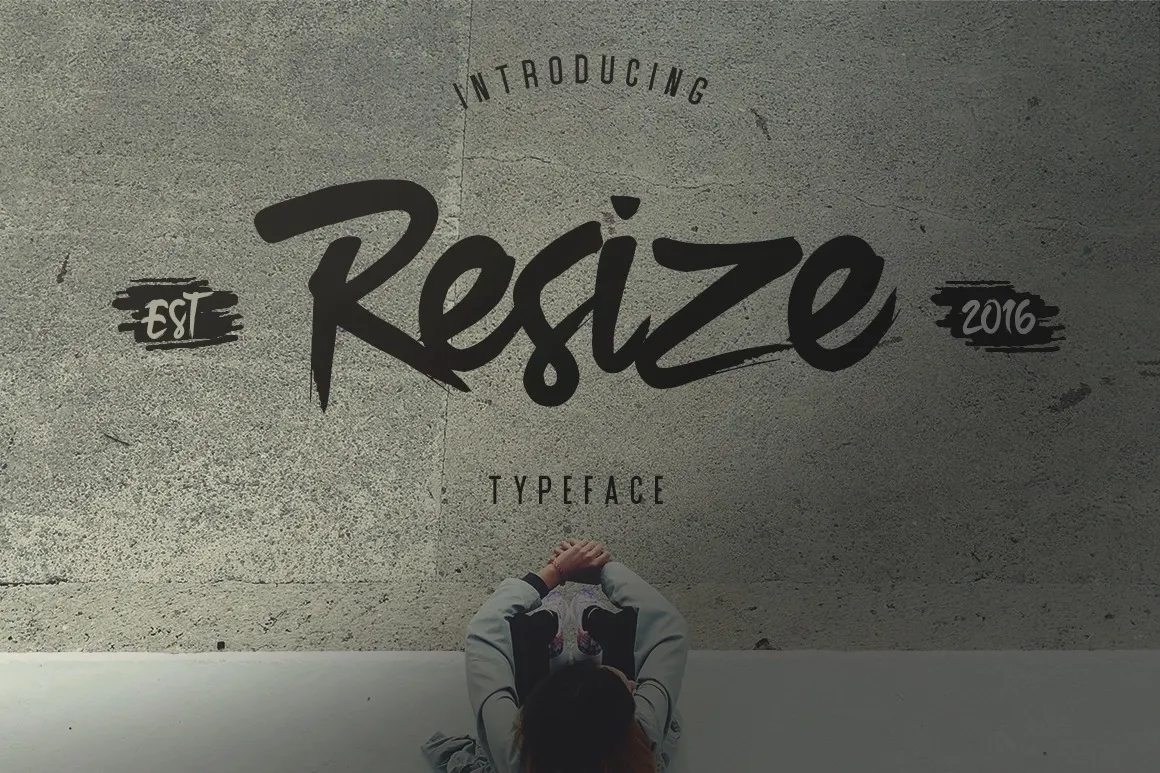
Esta fonte foi criada pelo designer sizimon e é perfeitamente adaptada para aplicações que exijam destaque visual. Seu traço bold e estilizado é perfeito tanto para headlines, como para logotipos, assinaturas ou qualquer outra forma de design gráfico em destaque. Foi concebida para se destacar na cena do design, seja ele no mundo das logos, onde a formalidade é importante, até nos projetos mais pessoais como cartões de convite e cards de casamento. Ideal também para aplicação em materiais impressos formais, como envelopes, logotipos, revistas, livros, cartões de lembrança, embalagens, moda, maquiagem ou material de escritório. A sua elegância transmite confiabilidade e estilo, tornando-a uma opção ideal para qualquer projeto que valorize a qualidade e o design cuidadoso. A fonte é perfeita tanto para trabalhos profissionais formais quanto para expressar personalidade em criações mais criativas e despojadas.